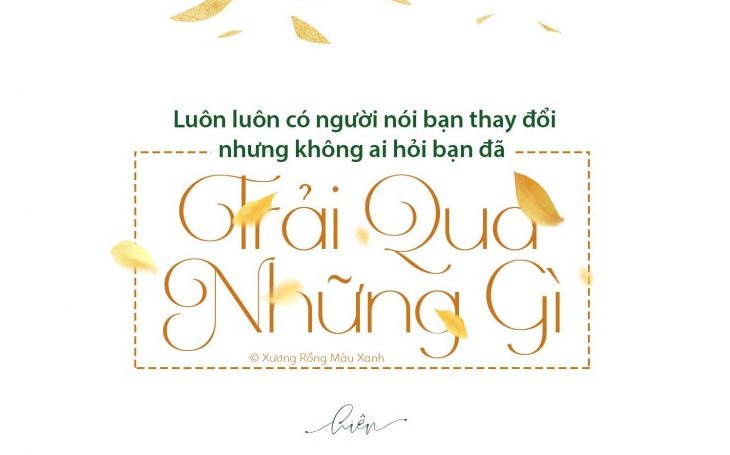
Font viêt hóa MTD Elipses
Giới thiệu về Font viêt hóa MTD Elipses
Trong thế giới thiết kế đồ họa hiện đại, việc lựa chọn một Font Miễn Phí phù hợp là yếu tố then chốt giúp tác phẩm trở nên nổi bật. Font viêt hóa MTD Elipses là một bộ phông chữ độc đáo, mang phong cách hiện đại và thanh lịch, rất được ưa chuộng tại Việt Nam. Được đội ngũ MTD chuyển ngữ tỉ mỉ, bộ phông này giúp người dùng dễ dàng gõ tiếng Việt có dấu mà không lo lỗi hiển thị, phù hợp cho cả người mới bắt đầu và các nhà thiết kế chuyên nghiệp.
Ưu điểm nổi bật của phông chữ MTD Elipses
Điểm ấn tượng nhất của Font viêt hóa MTD Elipses chính là sự kết hợp hoàn hảo giữa các đường nét mềm mại và cấu trúc hình học cân đối. Bộ phông này không chỉ mang lại cảm giác dễ đọc mà còn tạo nên tính nghệ thuật cao cho các ấn phẩm truyền thông. Nhờ tính đa dụng, bạn có thể sử dụng nó cho nhiều mục đích khác nhau như làm tiêu đề sách, thiết kế logo, banner quảng cáo hay các bài thuyết trình học tập sinh động.
Cách ứng dụng Font viêt hóa MTD Elipses hiệu quả
Sử dụng trong giáo dục và học tập
Đối với học sinh và giáo viên, việc sử dụng các mẫu chữ đẹp giúp bài giảng trở nên lôi cuốn hơn. Font viêt hóa MTD Elipses cực kỳ phù hợp để trang trí các slide báo cáo hoặc làm thiệp chúc mừng. Độ tương phản tốt giữa các nét chữ giúp học sinh dễ dàng theo dõi nội dung từ xa, đồng thời kích thích sự sáng tạo trong quá trình học tập hàng ngày.